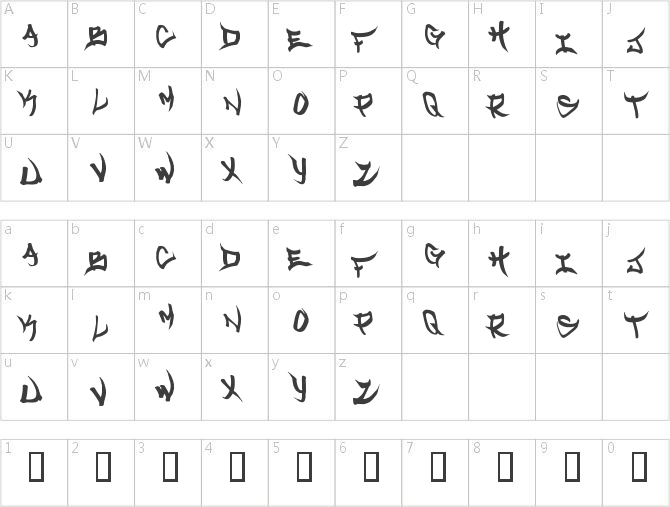
Welcome to Texas 詳情頁
Welcome to Texas字體字庫是一款讓人賞心悅目、百看不厭的英文字體,適合各類廣告和產(chǎn)品包裝設(shè)計(jì)應(yīng)用,字體大小0.03MB,格式為ttf字體,上傳用戶是眾聯(lián)齊成,作者/版權(quán)方為未知